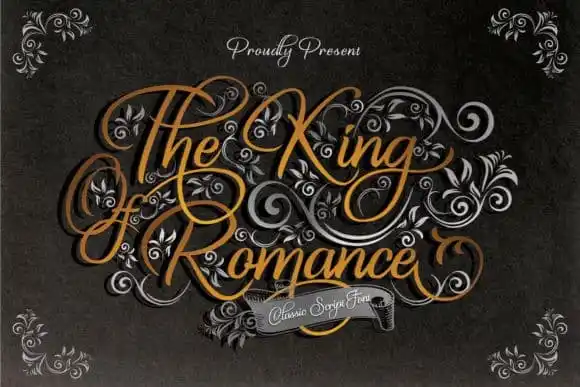
The King Of Romance Script Font – Download Grátis
A Fonte ‘The King Of Romance Script’ é uma criação artística ideal para quem busca uma elegância natural em sua tipografia. Desenvolvida pela creativework69, esta fonte se destaca por seu fluxo fluido e estilizado. Através do seu traçado cuidadosamente elaborado à mão, o tipo adquire um charme único que é perfeitamente adaptável para uso em diversos ambientes de design. Além disso, a inclusão de alternativas caracteres e ligaturas adiciona uma profundidade extra ao design, tornando-a ainda mais bela e versátil. A Fonte ‘The King Of Romance Script’ é uma fonte perfeita para personal branding, ideal tanto para criações pessoais quanto para eventos como casamentos. Suas linhas delicadas também são ideais para aplicações publicitárias, permitindo que você dê um toque de sofisticação a sua identidade visual ou à sua campanha de marketing. Tudo isso torna ‘The King Of Romance Script’ uma opção essencial para quem busca harmonia e elegância em seu design gráfico.